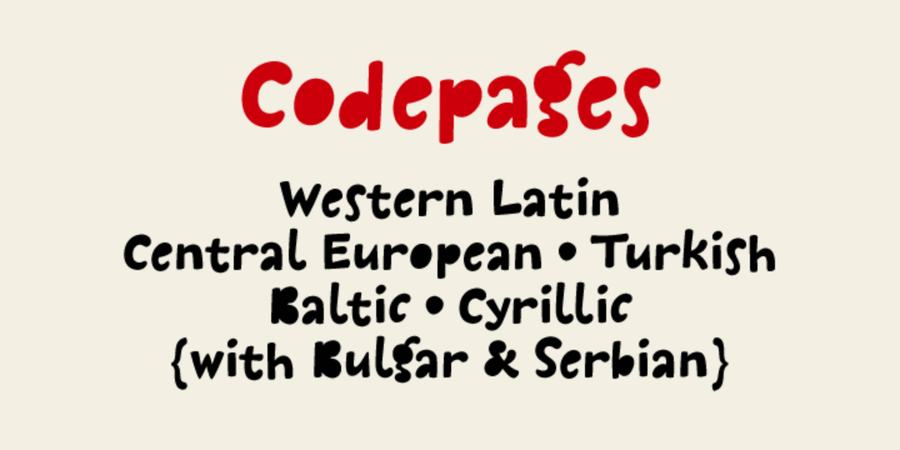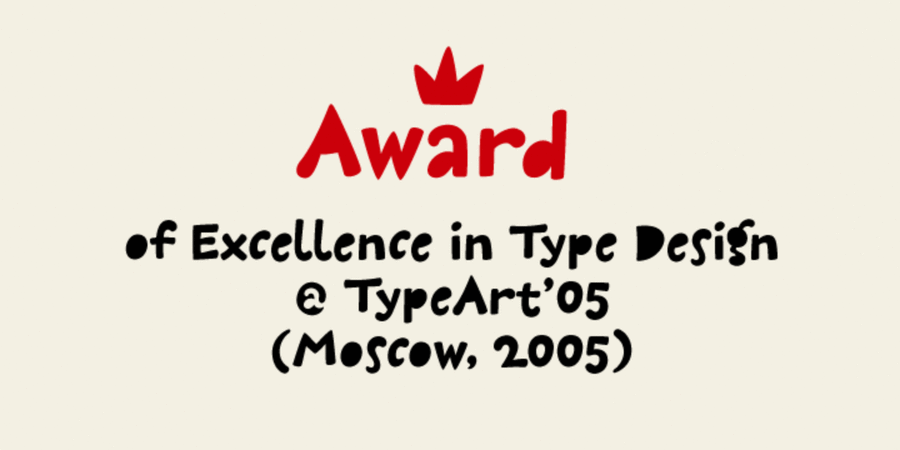
Бездіркова версія шрифту Галушки. М'який добрий і жартівливий шрифт, що ідеально підходить для коміксів, іграшок, дитячих книжок, упаковки та рекламної продукції. Цей шрифт розробив Дмитро Растворцев у 2005-2010 роках.